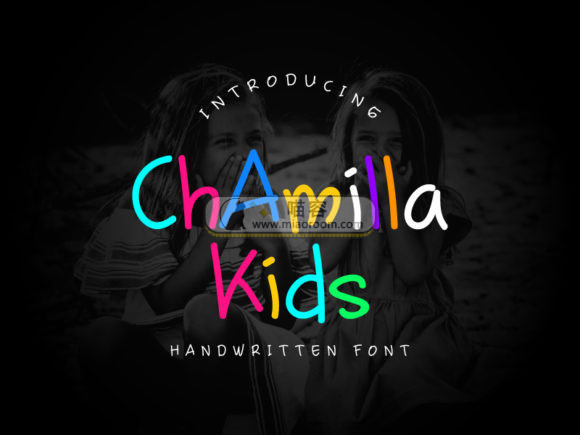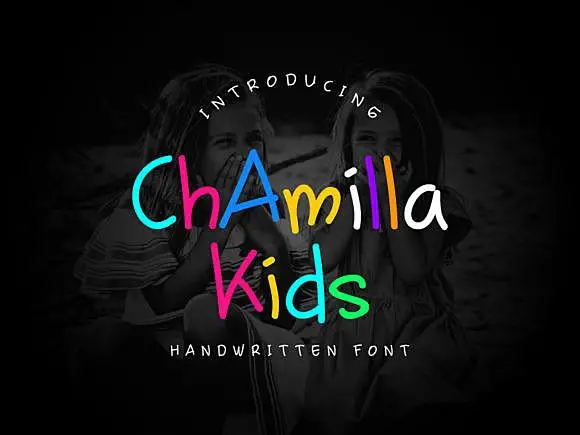
精美字体 21年1月19日 编辑 前往下载 喵容发布2号 取消关注 关注 私信 Chamilla Kids是一款美观而俏皮的手写字体,带有足够的醒目感。非常适用于儿童节、游乐园等儿童主题的设计作品。 相关文章: [系统字体] 25种打包精美无衬线字体(内附字体资源):之前我整理过衬线字体的合集,今天我分享的是无衬线字体。有人或许还搞不清楚这两种字体到底区别在哪里?其实衬线体与非衬线体的最大区别就是有无装饰性(有无边角)。无衬线字体常用于电子设备,iOS7、iOS …... [系统字体] 几何无衬线字体——NOAH:今天分享的一款系统字体NOAH具有细节清晰,布局独特的优点。它能够满足所有的印刷要求,如果需要的朋友可以到文末下载哦! 下载权限查看 ¥ 免费下载 评论并刷新后下载 登录后下载 查看演示 {{attr.name}} …... [系统字体] 具有现代简约感的字体——axton:Axton是一款令人难以置信的圆润无衬线字体,具有现代和简约的感觉。它能让我们的作品脱颖而出。需要的朋友可以到文末进行下载哦! 下载权限查看 ¥ 免费下载 评论并刷新后下载 登录后下载 查看演示 {{attr. …... [系统字体] 美观独特的字体:wish:Wish字体具有独特有趣的波浪笔触,非常适用于品牌,标题,服装,海报,邀请函设计等等。 喵容——wish字体1喵容——wish字体2 下载权限查看 ¥ 免费下载 评论并刷新后下载 登录后下载 查看演示 {{attr.name}}: …... [系统字体] 实用与独特集于一身的笔刷字体:资源名称 Atmosphere 资源大小 1.07mb 资源格式 ttf、jpg 资源简介 Atmosphere字体具有非常真实的画笔纹理,此字体具有所有大小写字符、数字以及标点。非常适用于品牌设计、包装设计等。 喵容——Atmosphere …... [系统字体]独特的复古字体—Coconut Inline Grunge:资源描述 字体 资源名称 独特的复古字体—Coconut Inline Grunge 资源格式 otf、ttf、jpg 资源大小 619kb 资源简介 这款字体适用于各种印刷项目,徽标,T恤,杂志封面,海报设计等。 可免费用于个人和商业用 …... 下载权限查看 ¥ 免费下载 评论并刷新后下载 登录后下载 查看演示 {{attr.name}}: 您当前的等级为 登录后免费下载登录 小黑屋反思中,不准下载! 评论后刷新页面下载评论 支付¥以后下载 请先登录 您今天的下载次数(次)用完了,请明天再来 支付积分以后下载立即支付 支付以后下载立即支付 您当前的用户组不允许下载升级会员 您已获得下载权限 您可以每天下载资源次,今日剩余次 声明:本文为原创作品,版权归作者所有。未经许可,不得转载或用于任何商业用途。如若本站内容侵犯了原著者的合法权益,可联系我们进行处理。 给TA打赏 共{{data.count}}人 人已打赏 chamilla kids俏皮儿童